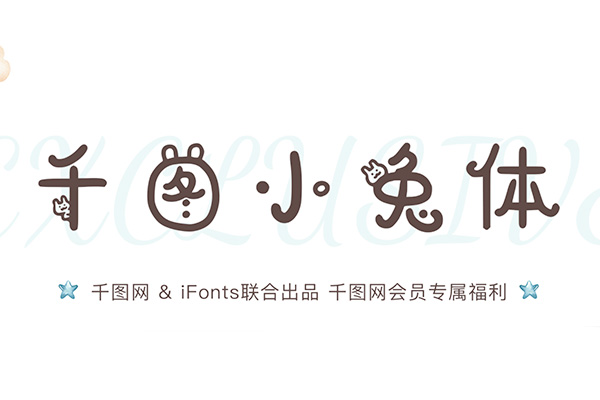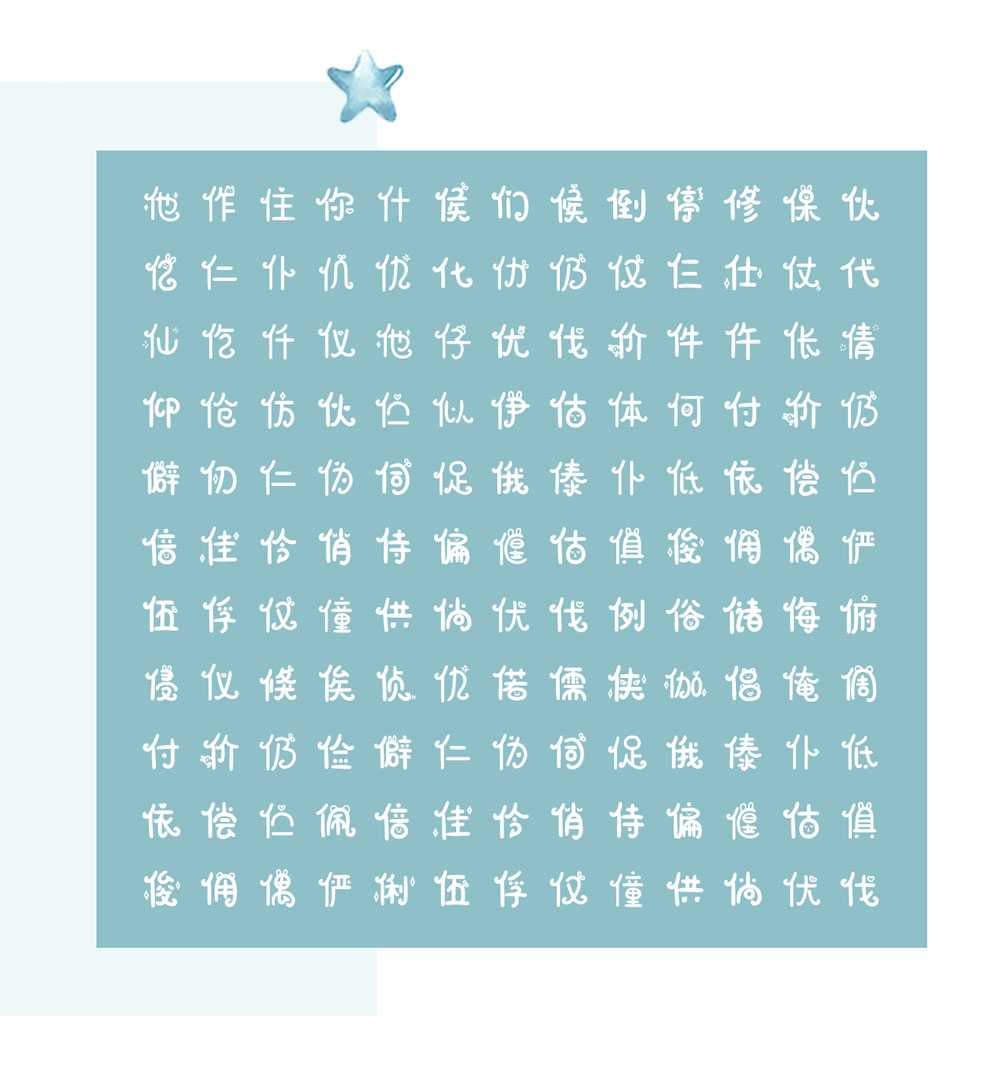
千图小兔体
千图小兔体是千图网(http://www.58pic.com)与国内专业的字体设计机构iFonts共同发布的一款萌系创意字体,经过长达半年多的精心研发与制作,现已向所有千图网用户免费开放下载。这款字体巧妙地将可爱的千小兔元素融入到字体设计中,彰显出年轻、活力与俏皮的特质,适用于打造可爱、少女风格的海报、店招等场景。
千图小兔体效果预览
千图小兔体字体效果预览